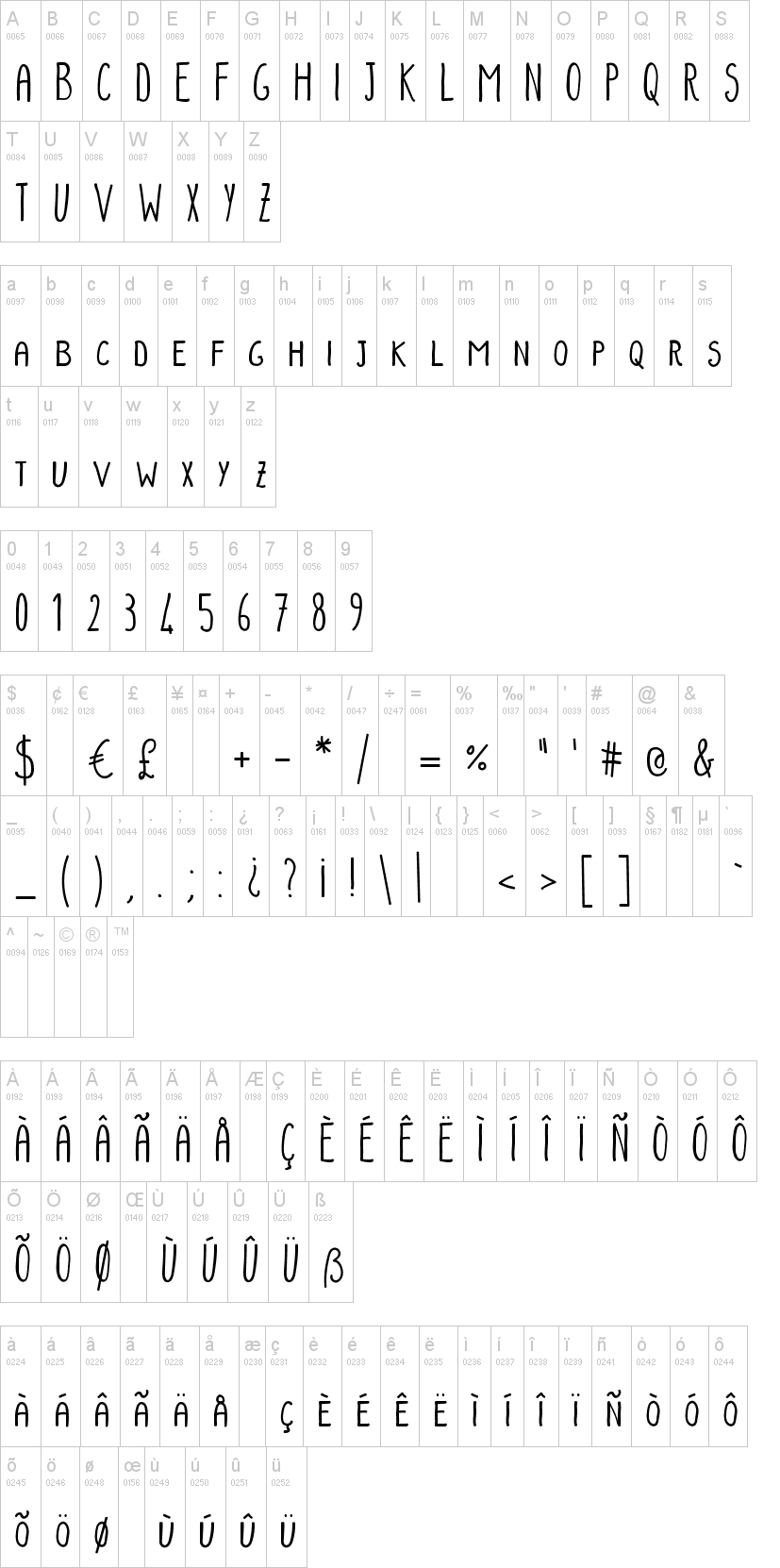
Potatoes And Peas
Potatoes And Peas 是一款由 Fontfabric 公司设计的字体,它是一种现代活泼的手写字体,由英文字母、数字和标点符号组成。它具有轻松活泼的特点,可以提供您创造力无限的设计灵感。Potatoes And Peas 字体适用于各种类型的项目,包括广告、商业、婚礼、海报、卡片等,能够为您的设计添加活力和魅力。
Potatoes And Peas是一款非常不错的手写艺术字体,具有很好的视觉感,适合于文化类的宣传设计、商业类品牌的广告和产品包装设计以及个性化文字排版等较多场景。
Potatoes And Peas字符映射图